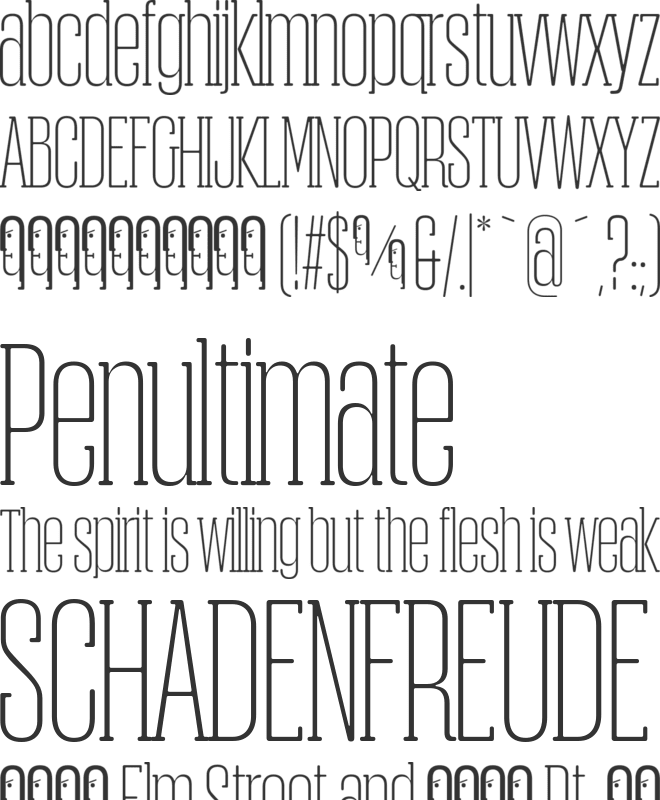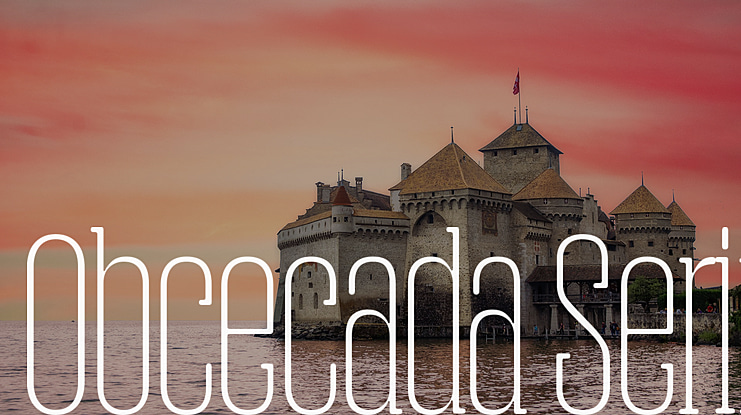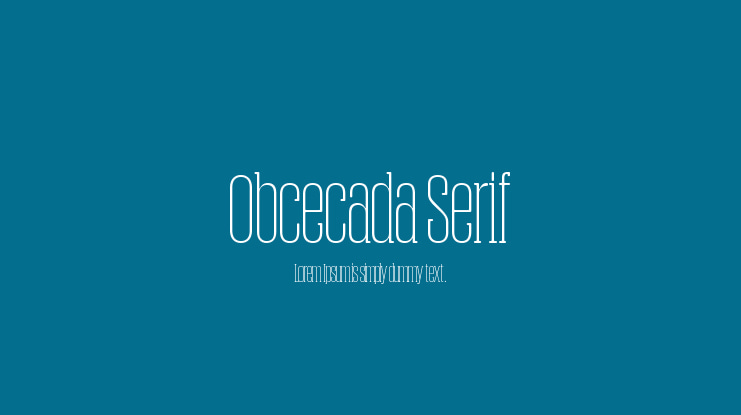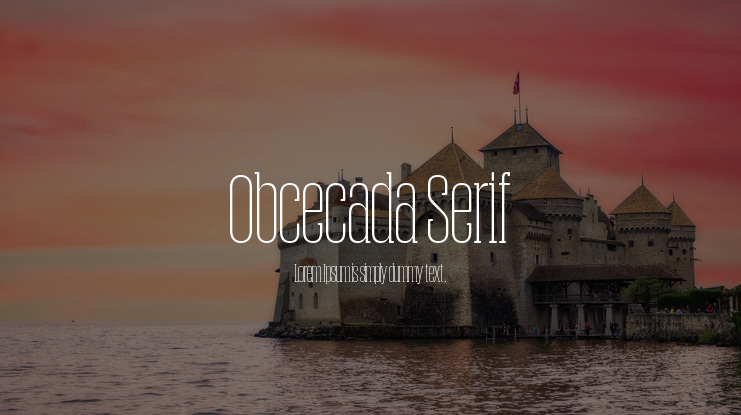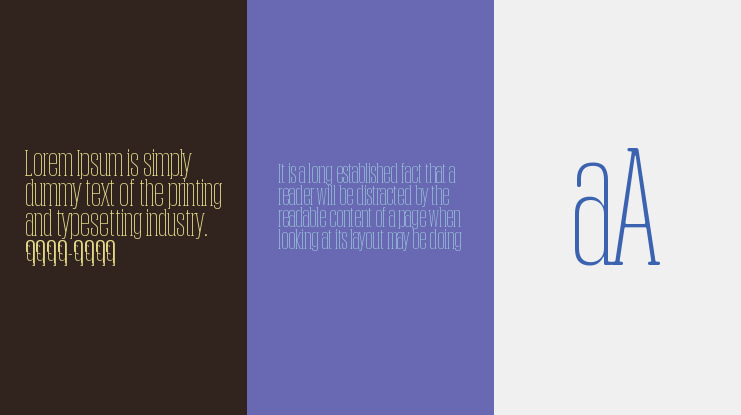
Obcecada Serif Font
Obcecada Serif es una tipografía geométrica slab serif muy condensada y fina con acabado redondeado en las astas y uniones con ascendentes y descendentes cortos.
Obcecada Serif is a very condensed geometric fine finish rounded slab serif typeface antlers and joints and falling short.
• Letras griegas
• Greek characters